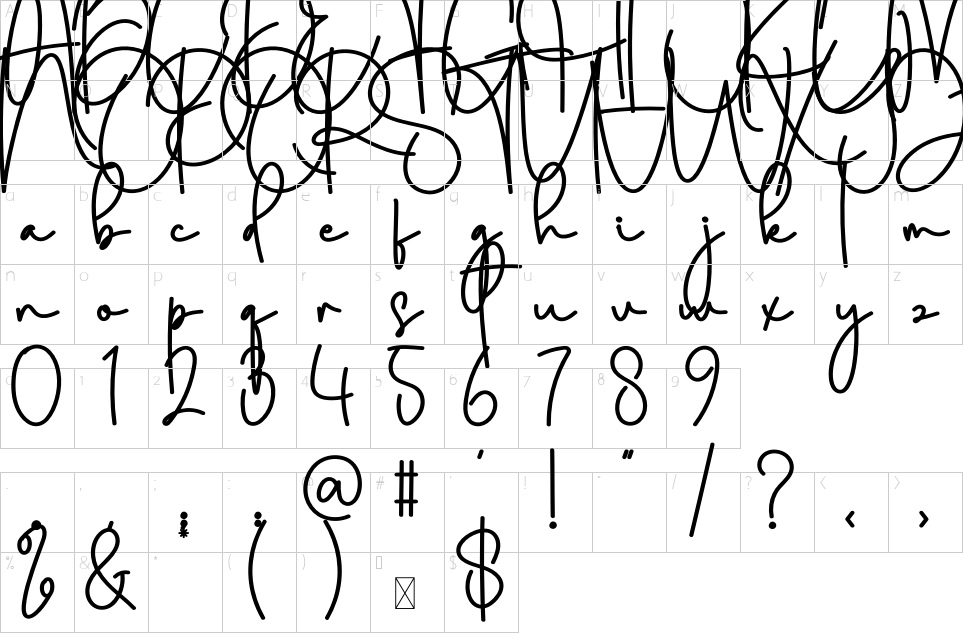
Daniel Signature Font
Descubra a elegância da Daniel Signature Font para seu próximo projeto visual com este download gratuito. Desenvolvida pelo designer scratchones, esta fonte vem em versões compatíveis tanto com Windows quanto com Mac. Seu design sofisticado e moderno será uma adição perfeita aos seus designs digitais ou impressos. Com 1210 downloads até agora, Daniel Signature não apenas oferece um amplo leque de opções para personalização, mas também se tornou uma escolha popular entre criativos. Se você está buscando criar algo único e atraente sem sair do conforto da sua casa ou escritório, esta fonte é a escolha perfeita. Não espere mais, instale Daniel Signature agora e inova!
Mapa de caracteres da fonte Daniel Signature Font